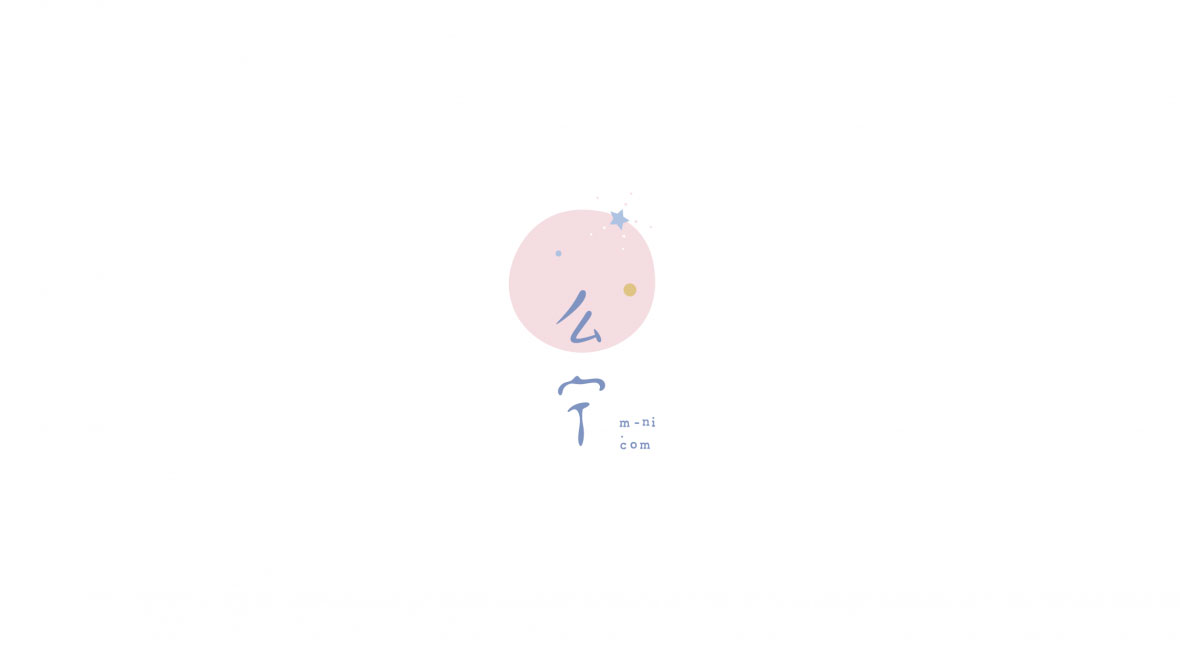
弘弢设计 | 四年logo案例回顾
以二十一个案例总结一下4年来自己的成长。精致、细腻、唯美、东方美学、人文气息,这是同行给我的标签,日本JTA、日本IPT、美国CA、香港DFA优异奖、台湾Golden标章奖、深圳SDA提名奖、上海SAGD评审奖…… 这是在业内知名赛事取得的成绩,更让我欣慰的是来自客户对我的信任与支持,能够给予我足够的创作空间,我能做到的最好的回馈,就是超越客户的预期,用自己的专业知识帮助客户解决品牌发展中遇到的问题,这种成就感与价值感,让人觉得再辛苦的付出都是值得的。 从第一个女装品牌−梨花季,第一个民宿项目−羽立舍,第一个本土乐队−旁白,到第一个美国项目−有米真好,从最北额尔古纳项目−蒙尔沁,到最南广州项目−火宅,客户的领域从服饰、餐饮、民宿、酒店、艺术机构到城市IP,每一个新项目的开始,都是一次自我的学习的过程,去我执,探索、突破,寻找适合当代语境下东方美学的叙事方式,以人文关怀塑造品牌未来是自己坚持的方向。 四年,该毕业了吧,^_^,回顾四年的案例,全当交一份毕业设计吧…… 弘弢 2021.07.02